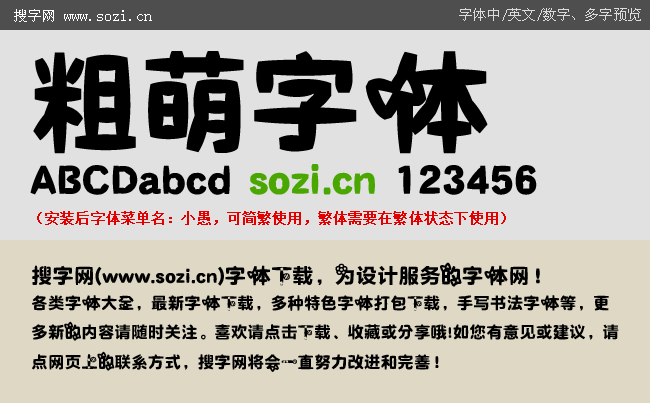
粗萌字體
搜字網(wǎng)給大家提供一款粗萌字體手機(jī)中文字體下載。這款手機(jī)字體是將粗黑體變形為POP風(fēng)格的藝術(shù)字體,字體嵌入了萌萌的的卡通圖案。是一款非常有趣的卡通藝術(shù)字體,特別適合喜歡手機(jī)字體個(gè)性一些的朋友在手機(jī)上安裝使用。